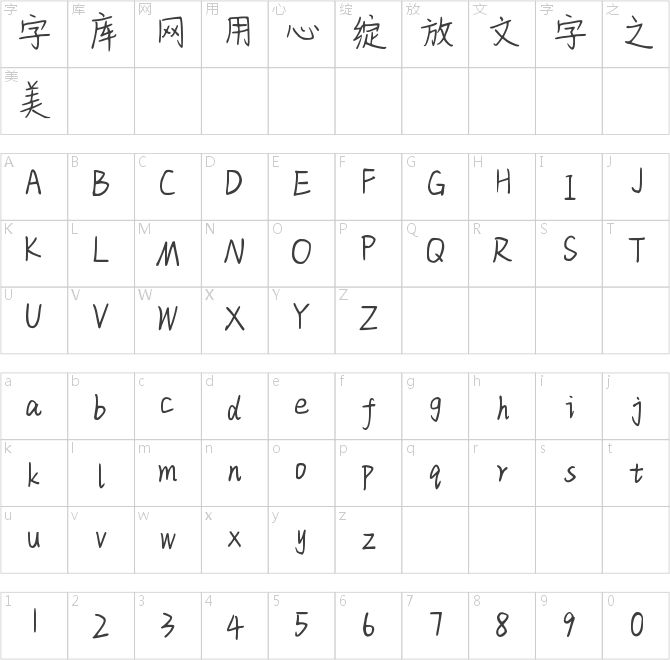
思雨
桔梗花語(yǔ)字體下載思雨桔梗花語(yǔ)
桔梗花語(yǔ)字體思雨桔梗花語(yǔ)字庫(kù)是一款讓人賞心悅目、百看不厭的中文字體,適合各類廣告和產(chǎn)品包裝設(shè)計(jì)應(yīng)用,字體大小3.85MB,格式為ttf字體,上傳用戶是一直在守護(hù),作者/版權(quán)方為思雨字庫(kù)